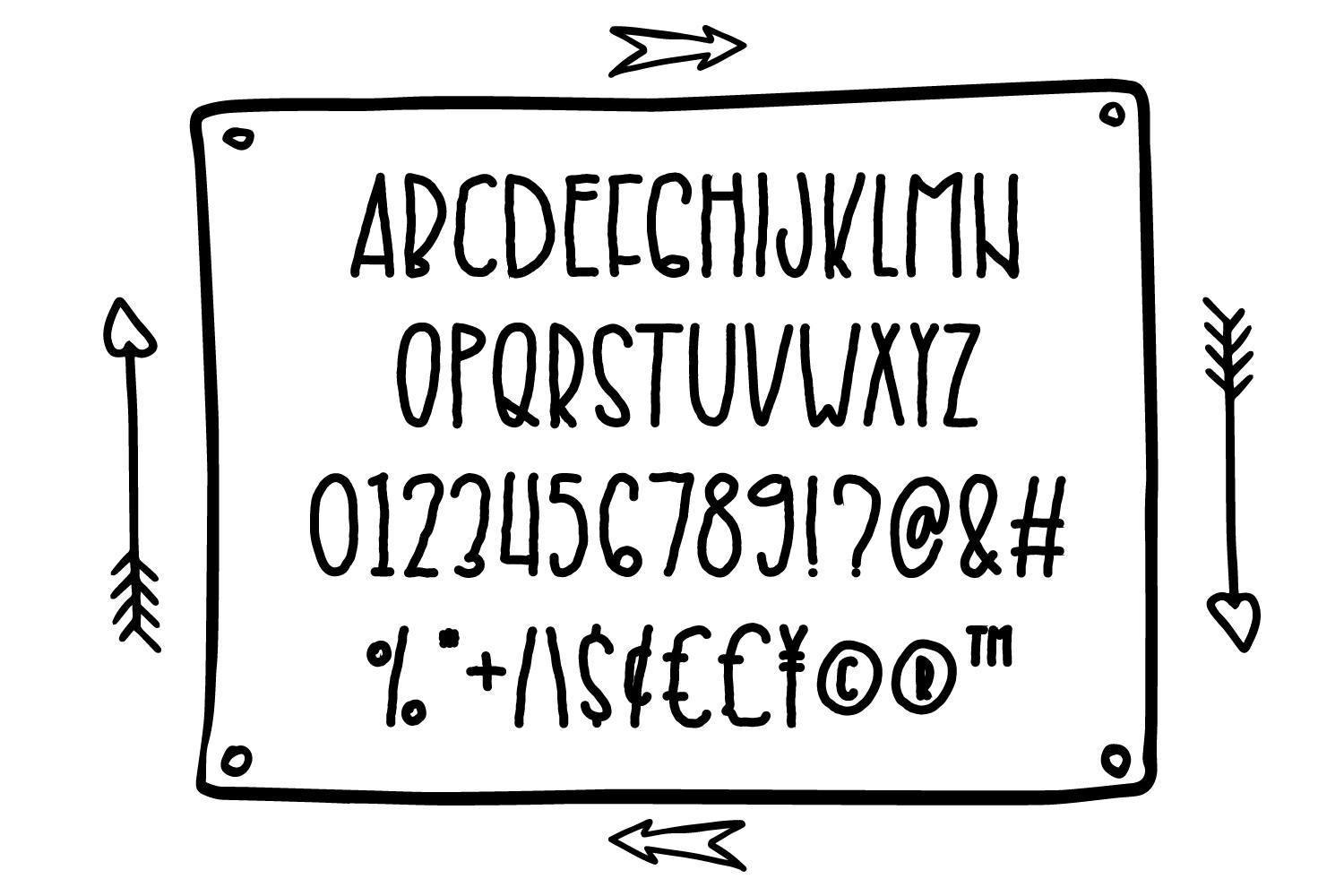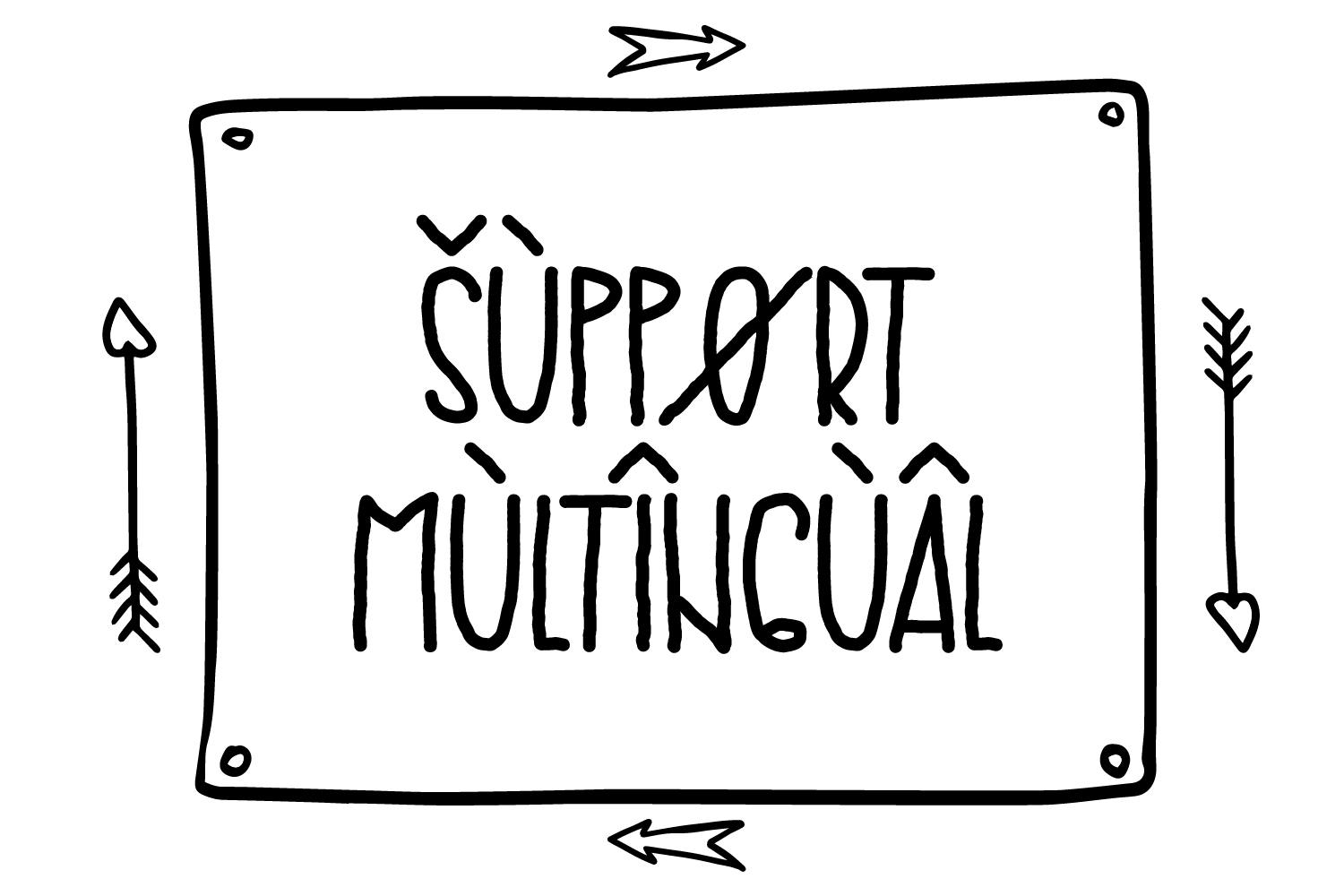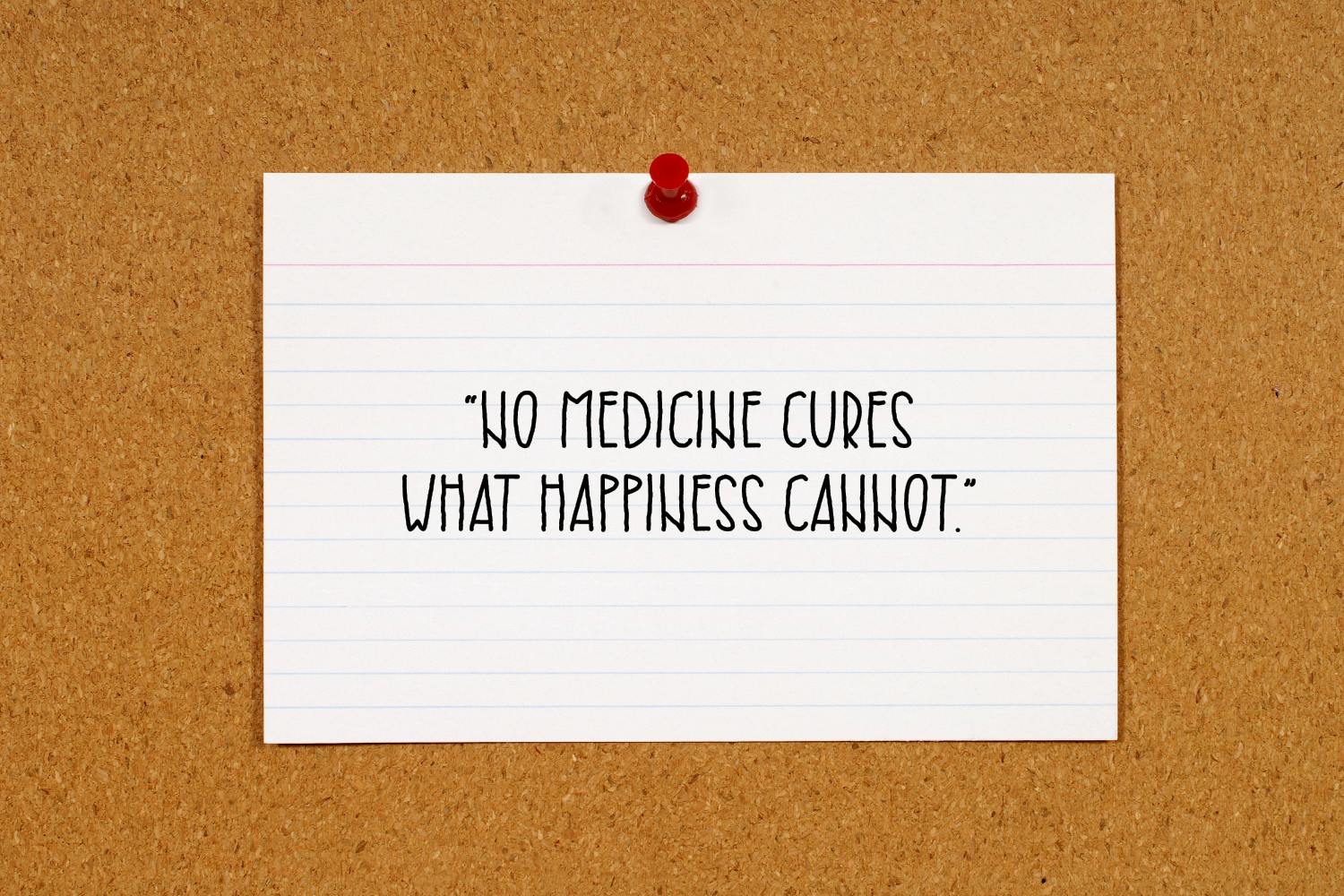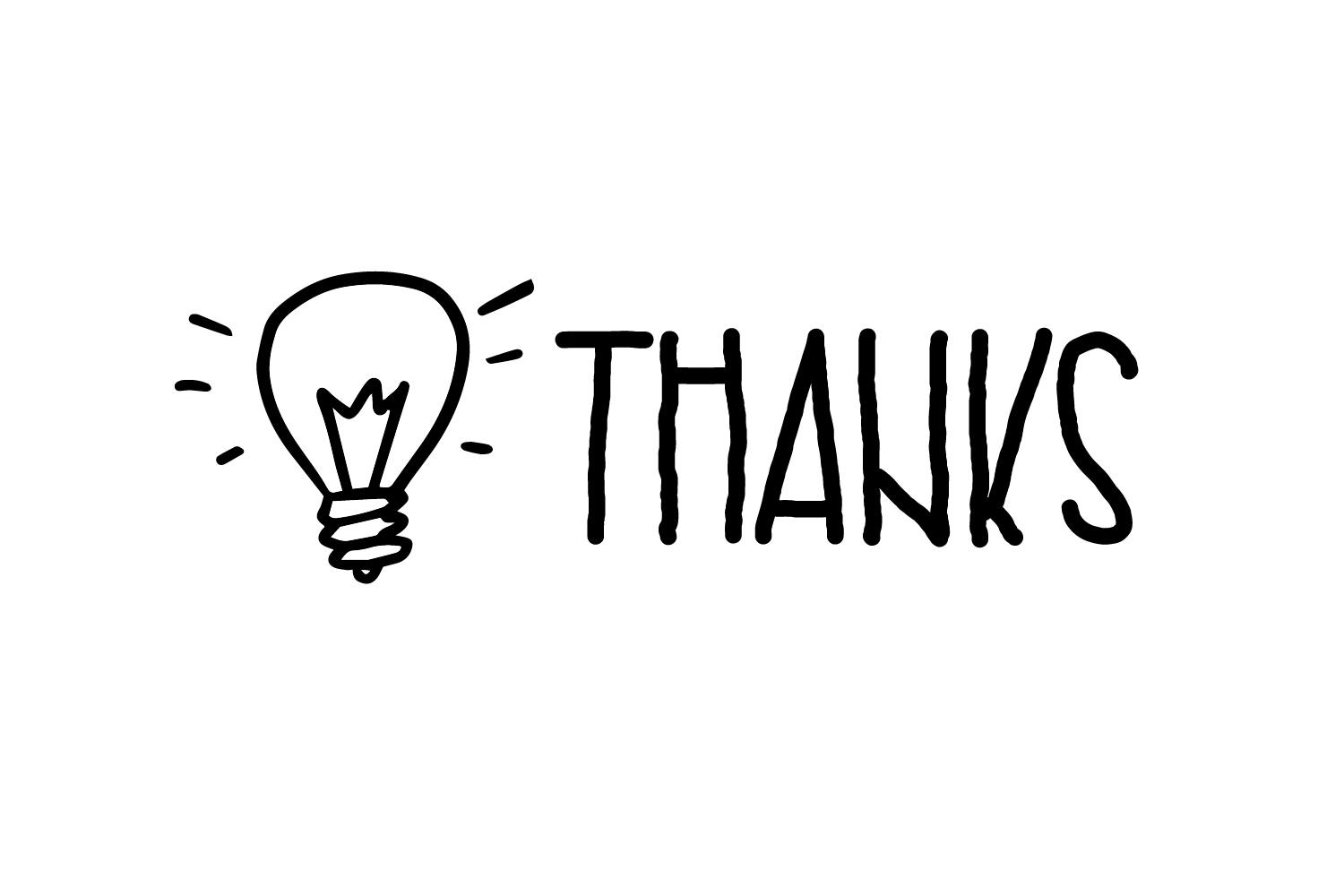
دانلود فونت نمایش جذاب Drawing Craft
Drawing Craft Cute Drawing Display Font
فونت نمایش کاراکترهای زیبا و شاداب مناسب برای طراحی‌های خلاقانه.
معرفی فونت نمایش Drawing Craft - فونت طراحی زیبا
فونت Drawing Craft یک فونت نمایش شیک و سرگرم‌کننده است. این فونت زیبا و دوستانه را به کتابخانه خود اضافه کنید و از آن در پروژه‌های مختلفی که نیاز به لمسه‌ای شاداب دارند، استفاده کنید.